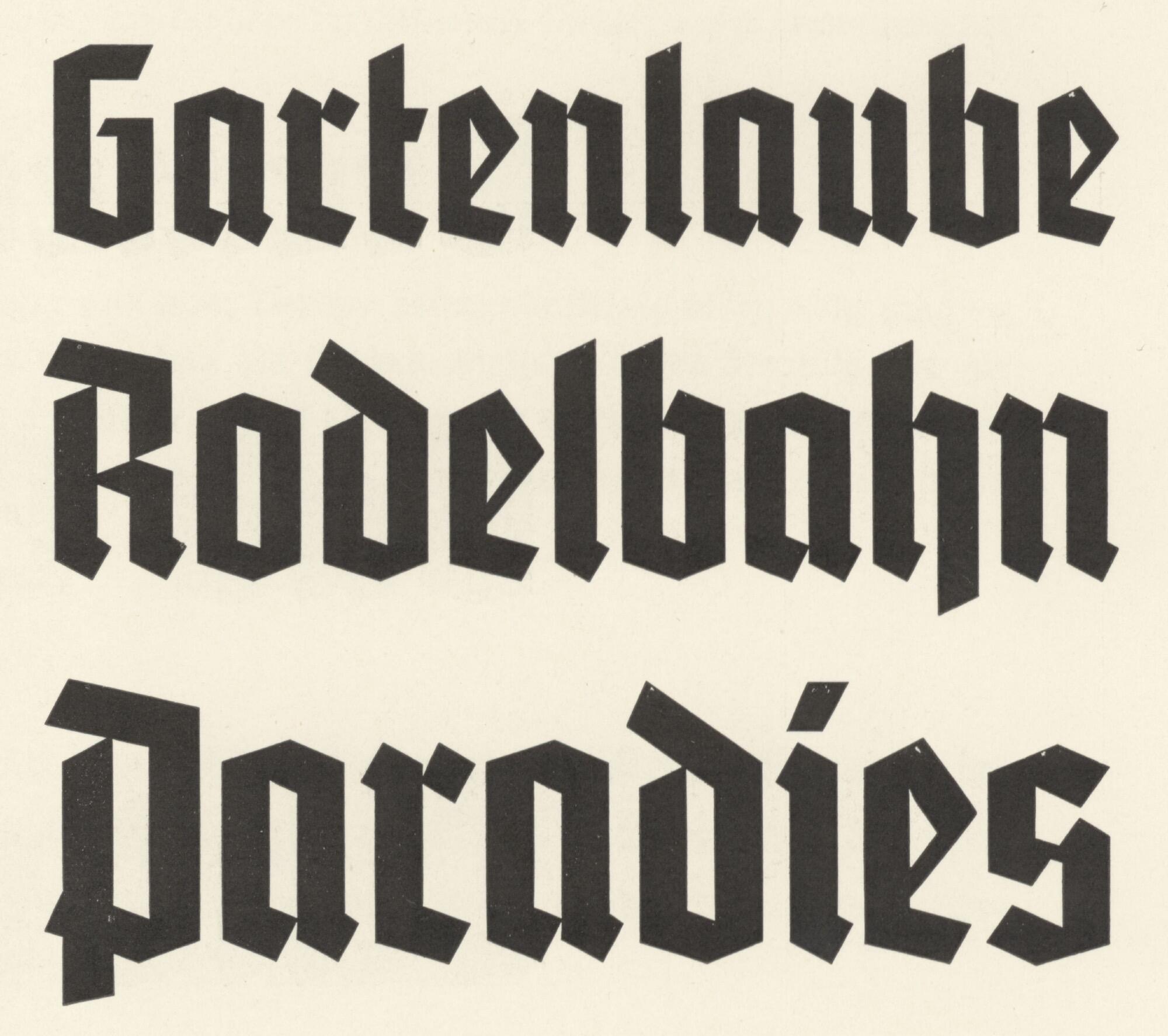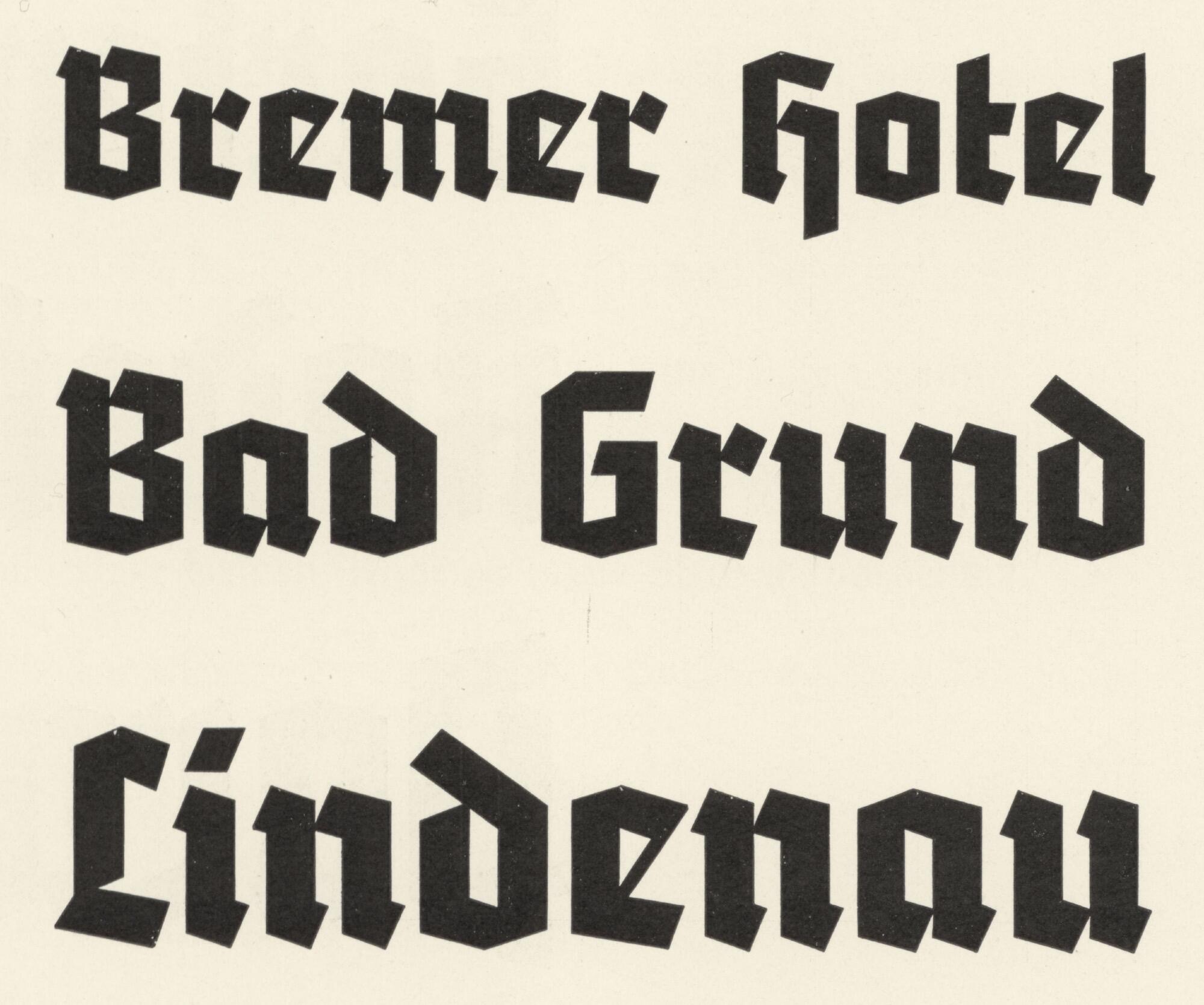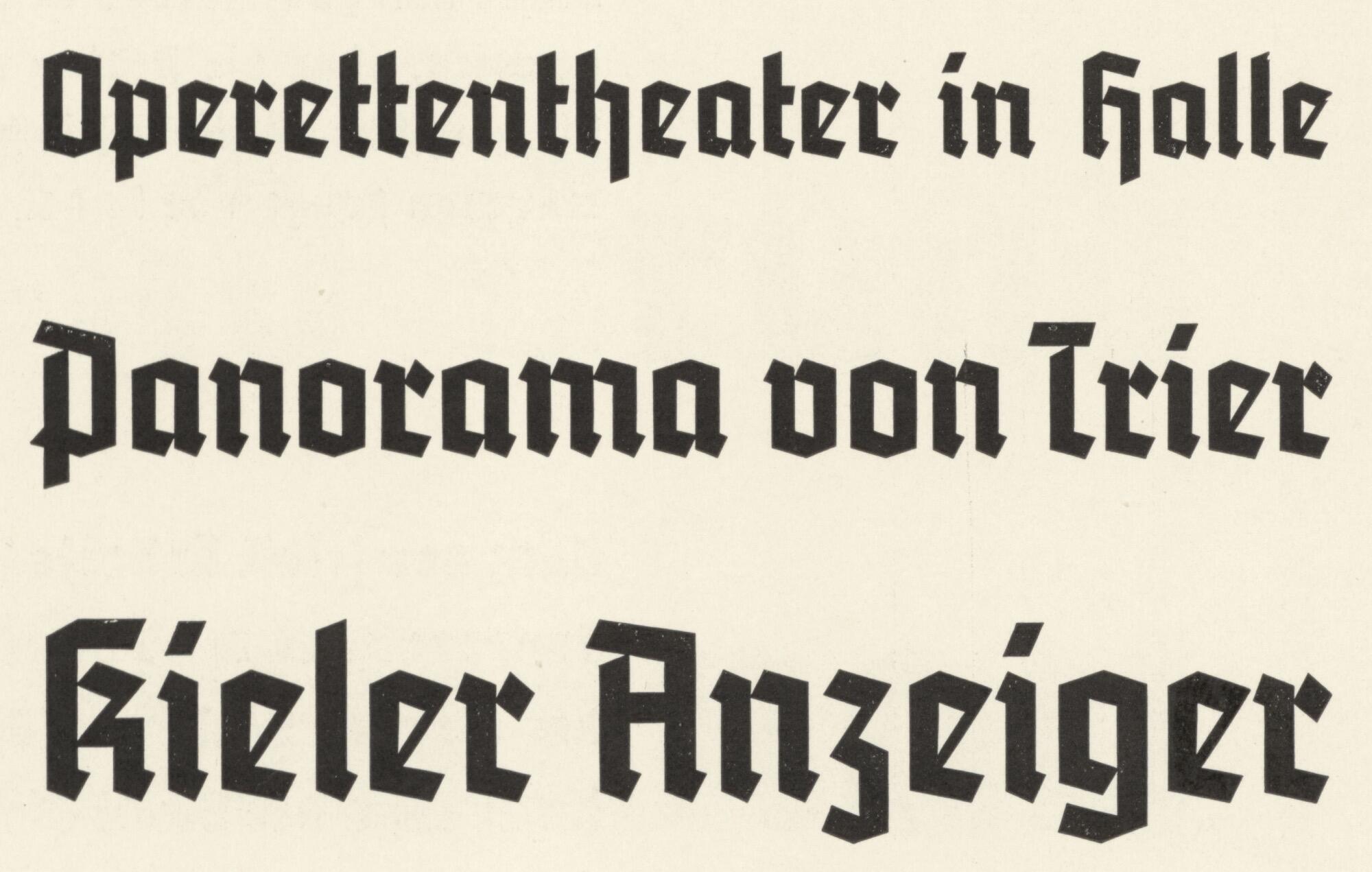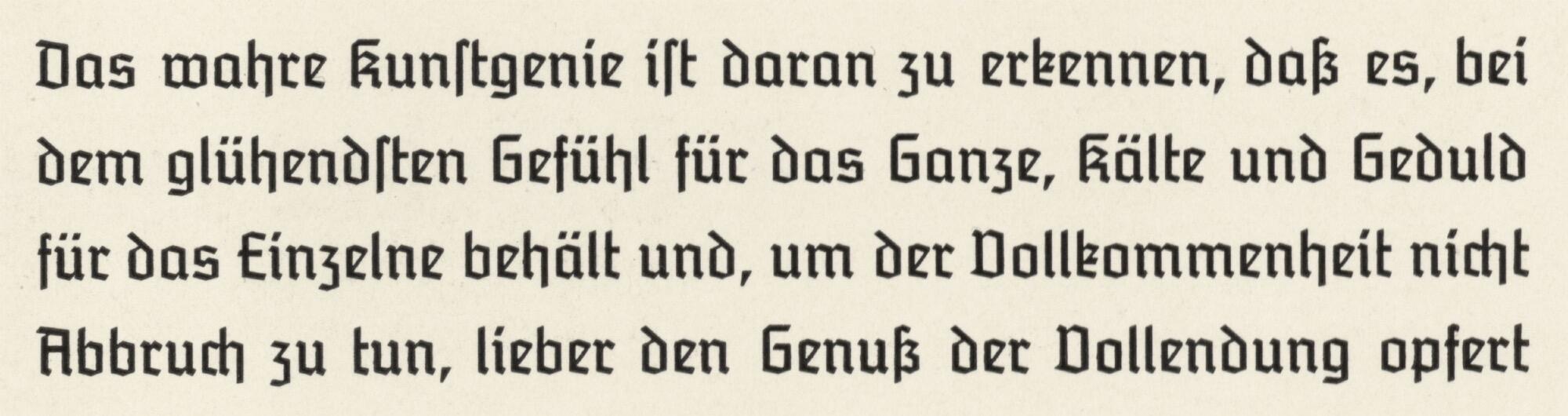
- 1934
- Gebrochene Schrift
Die Schriftart Potsdam ist eine gebrochene Groteskschriftfamilie von Robert Golpon und erschien 1934 bei der Hamburger Schriftgießerei J. D. Trennert & Sohn. Die Schriftgießerei C. E. Weber übernahm die Schrift ein Jahr später unter dem Namen Staufia, der vom Berg Hohenstaufen abgeleitet ist.
Die Versionen beider Gießereien waren in den vier Schnitten mager, halbfett, fett und schmalhalbfett erhältlich. Letzterer ist heute in einer kostenlosen Version von Manfred Klein und in einer kommerziellen Version von Gerhard Helzel erhältlich.
Originalmuster von C.E. Weber
Digitale Version von Manfred Klein